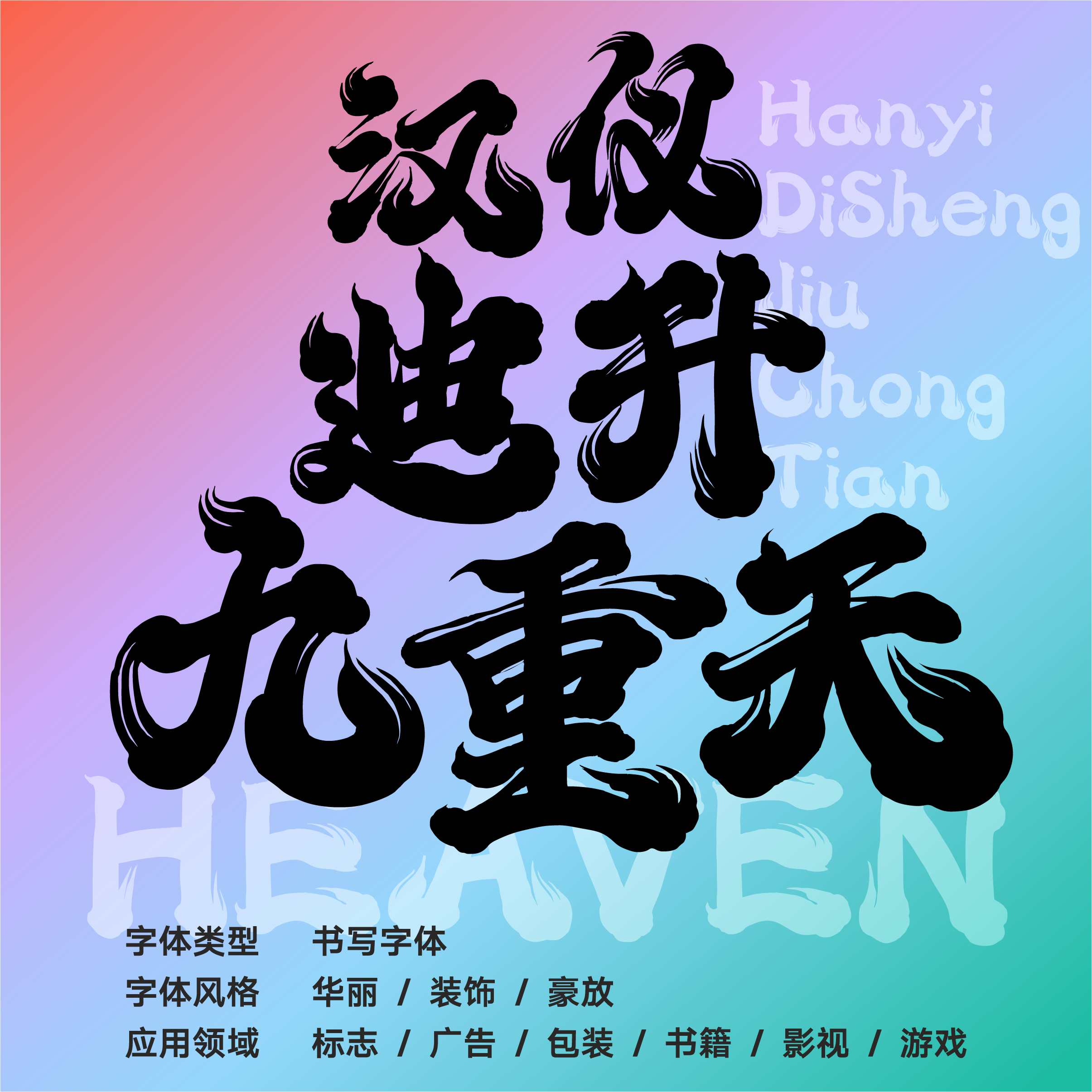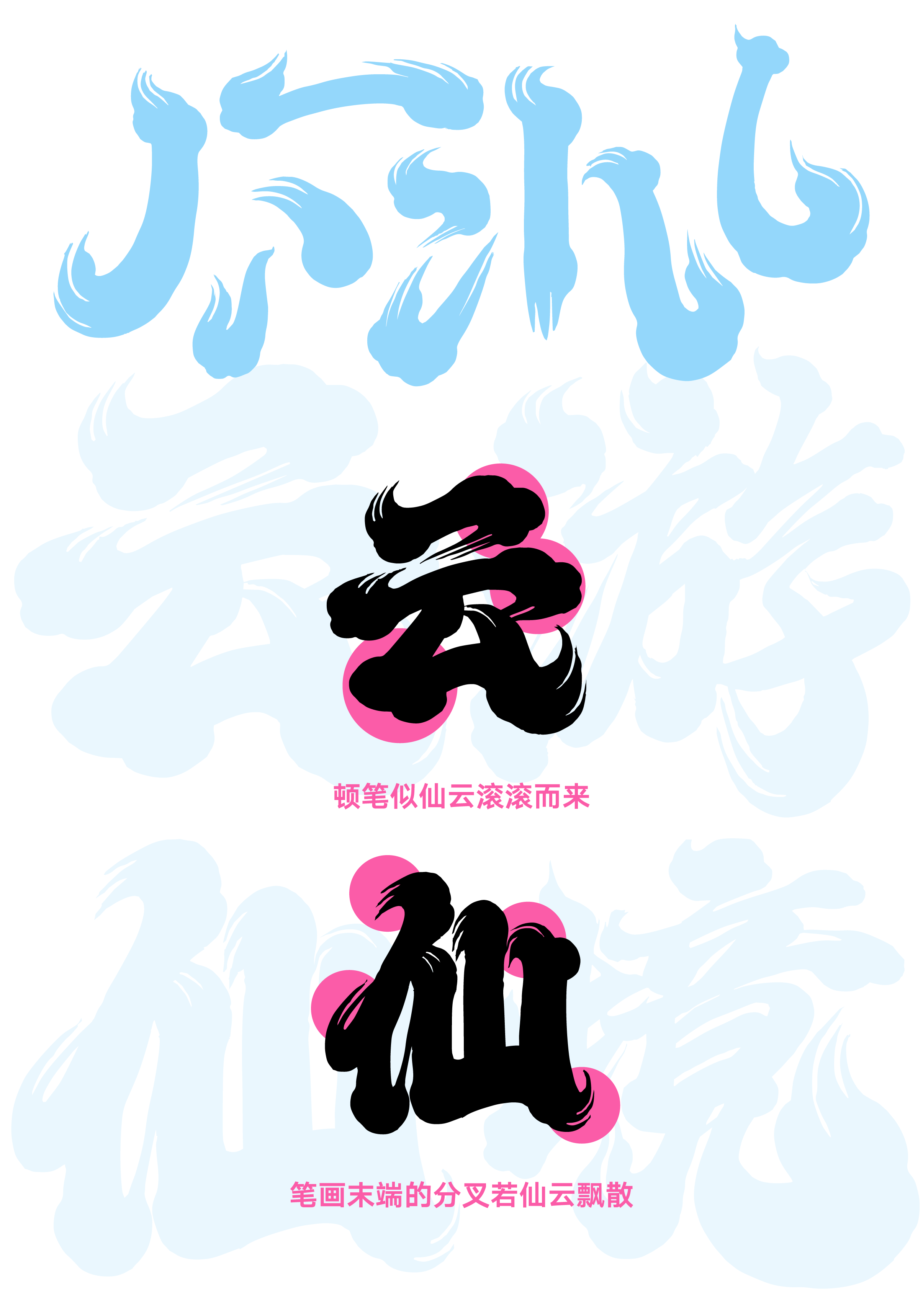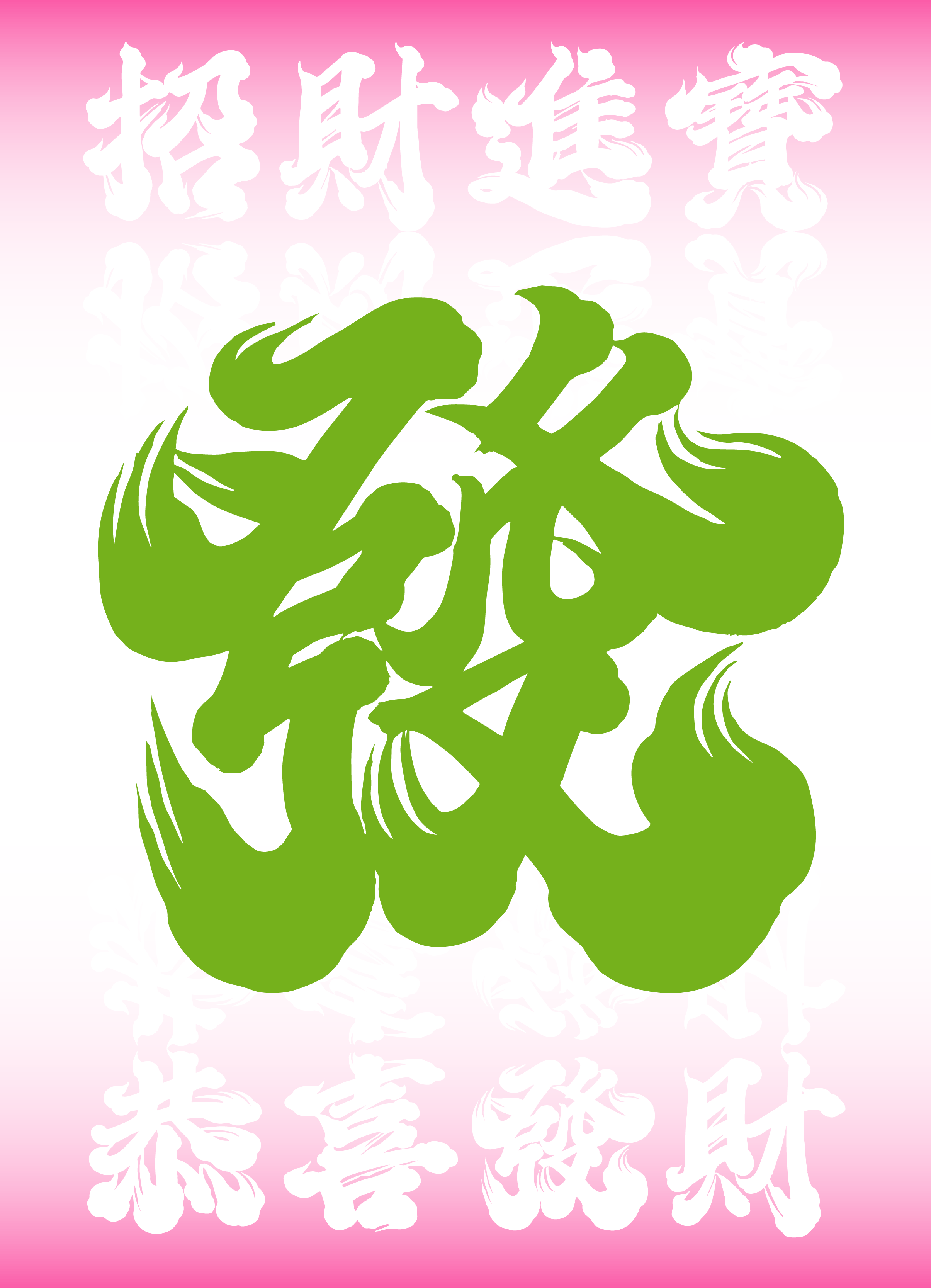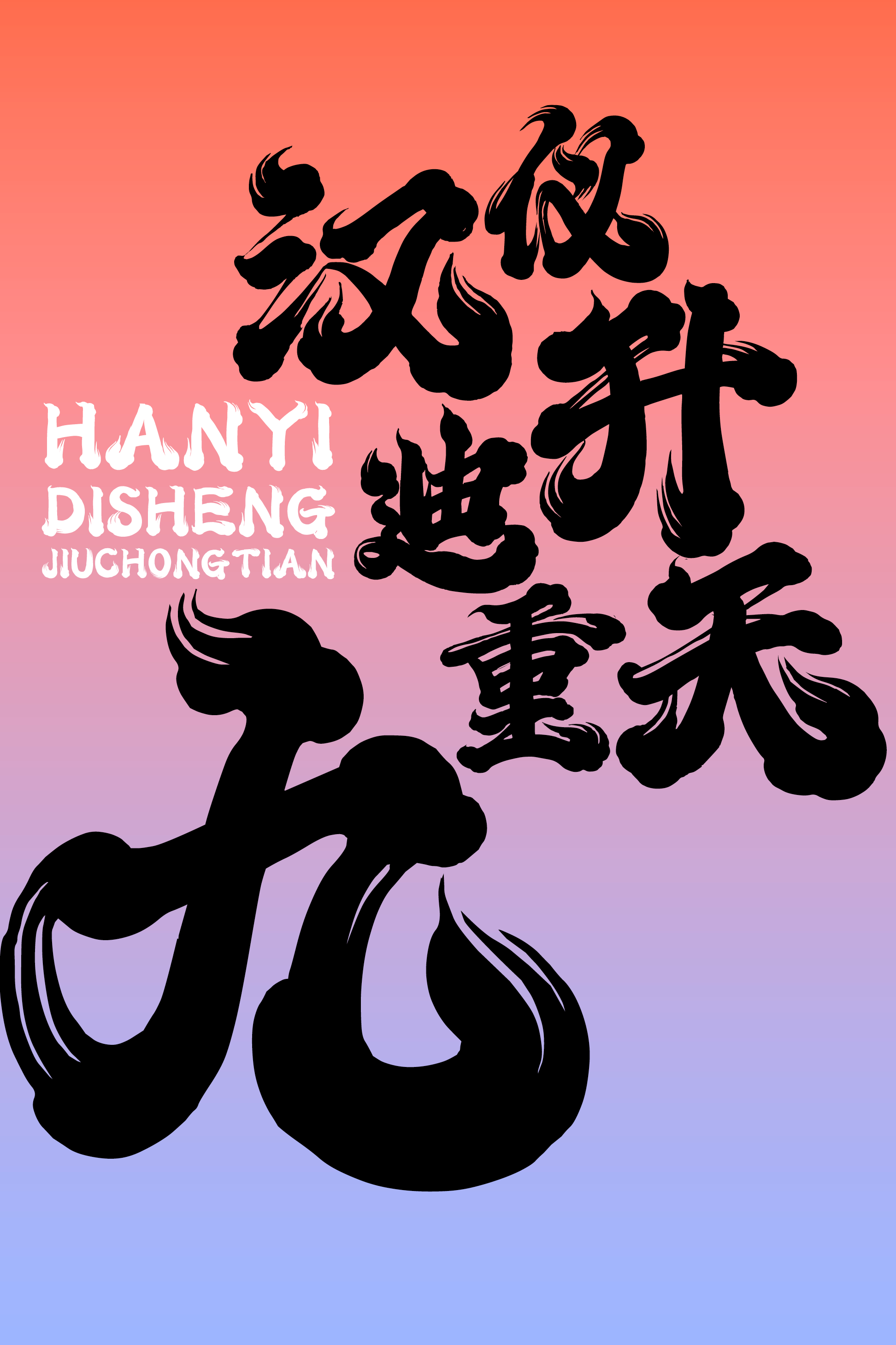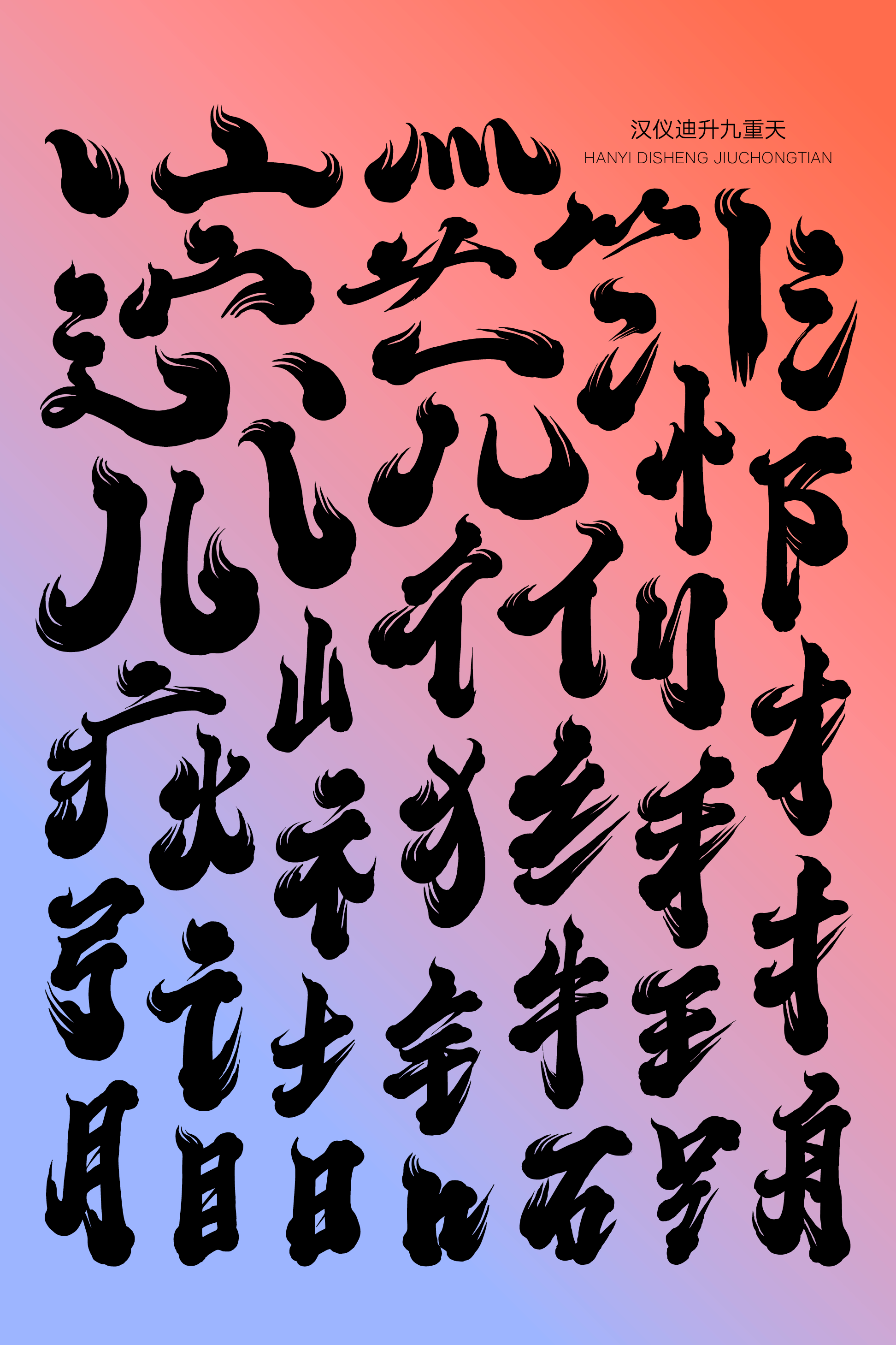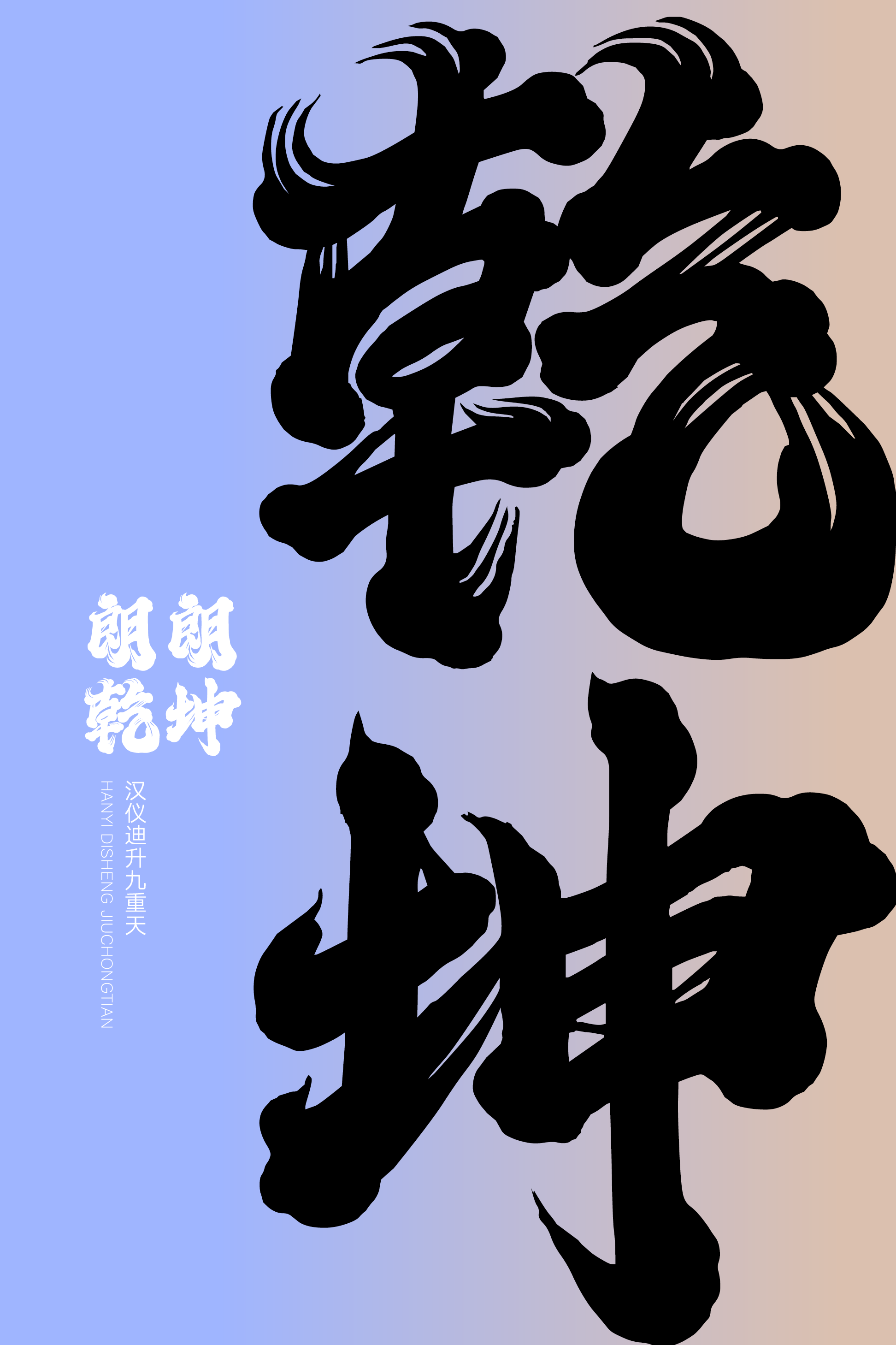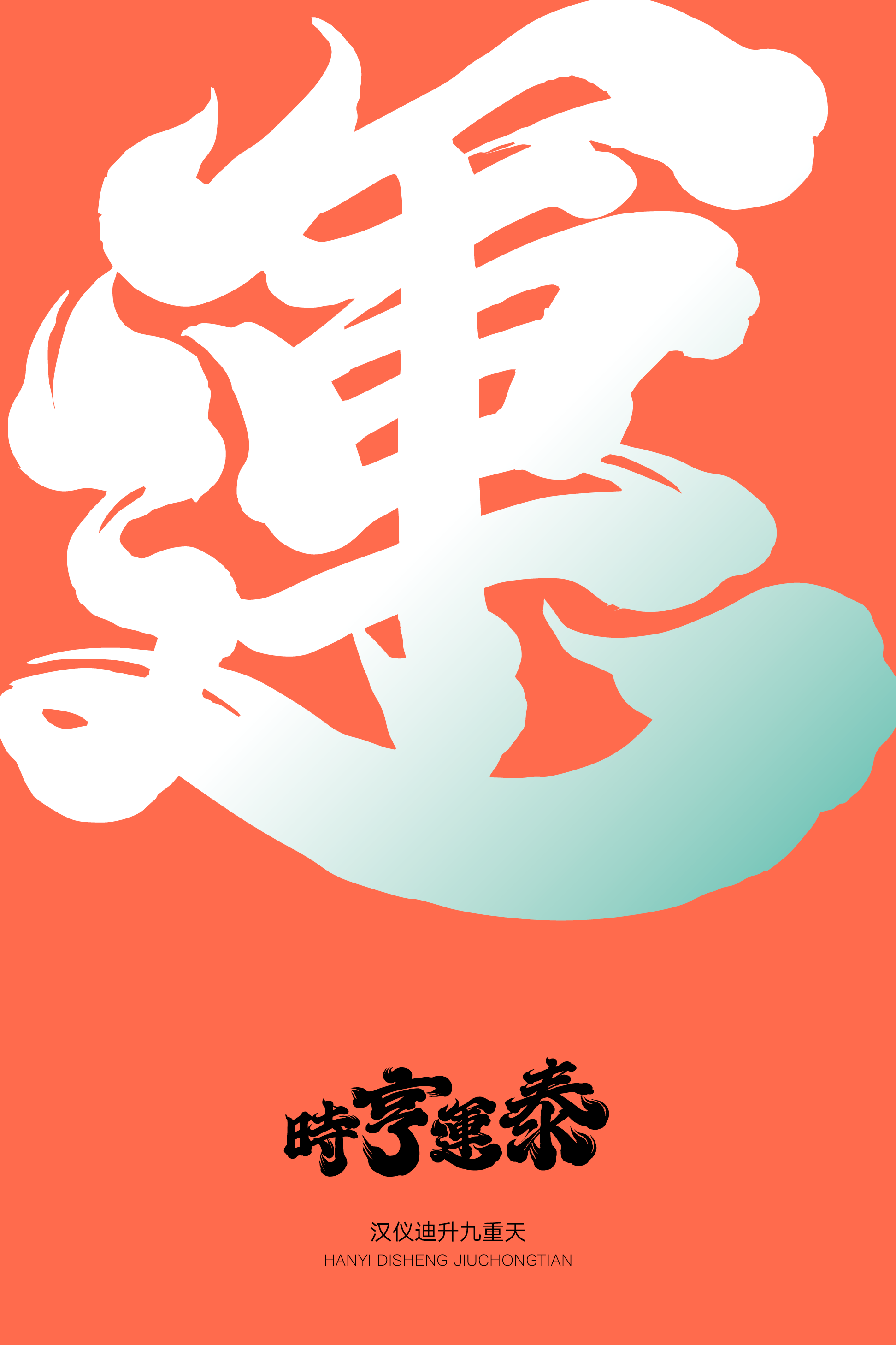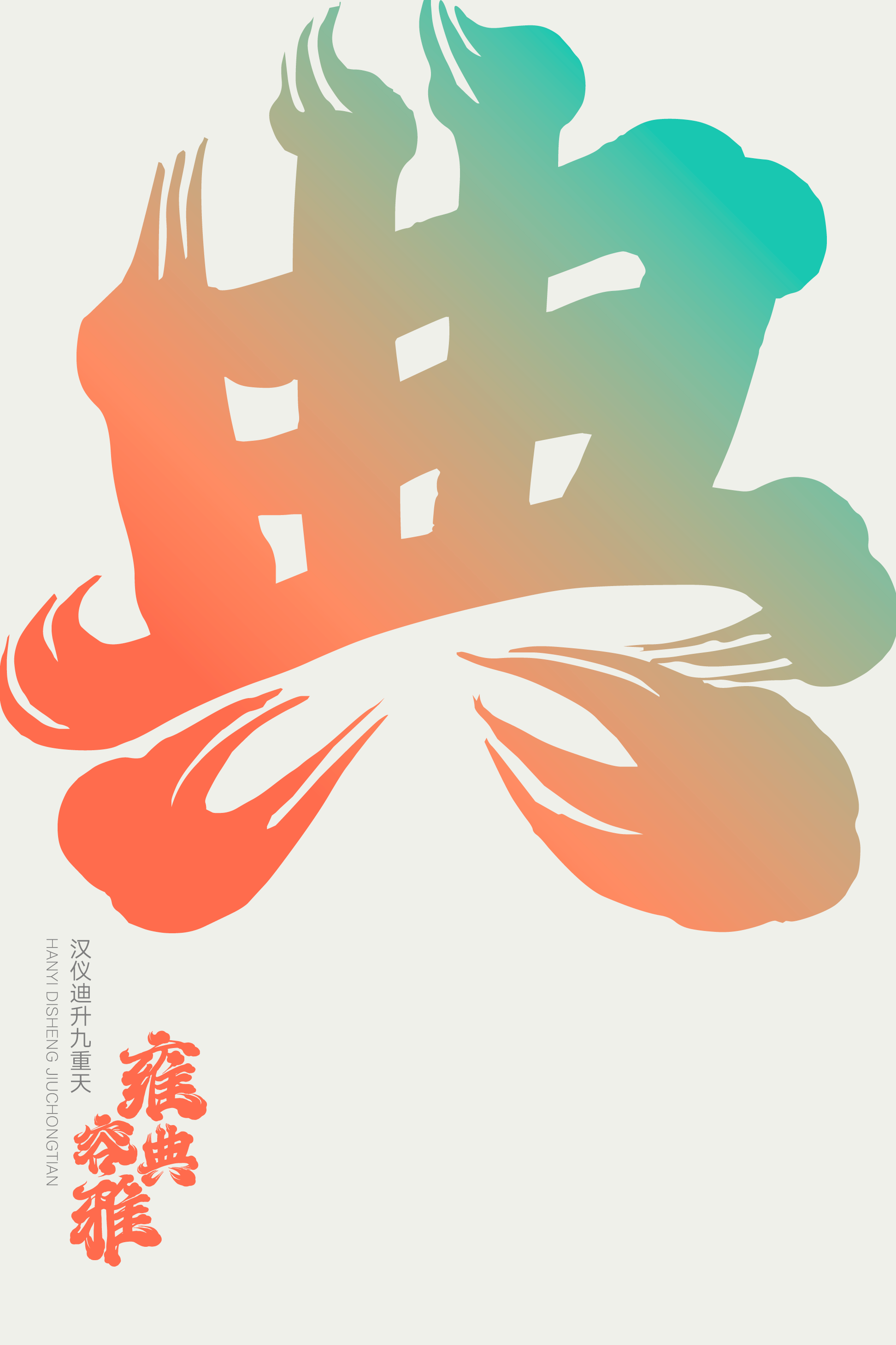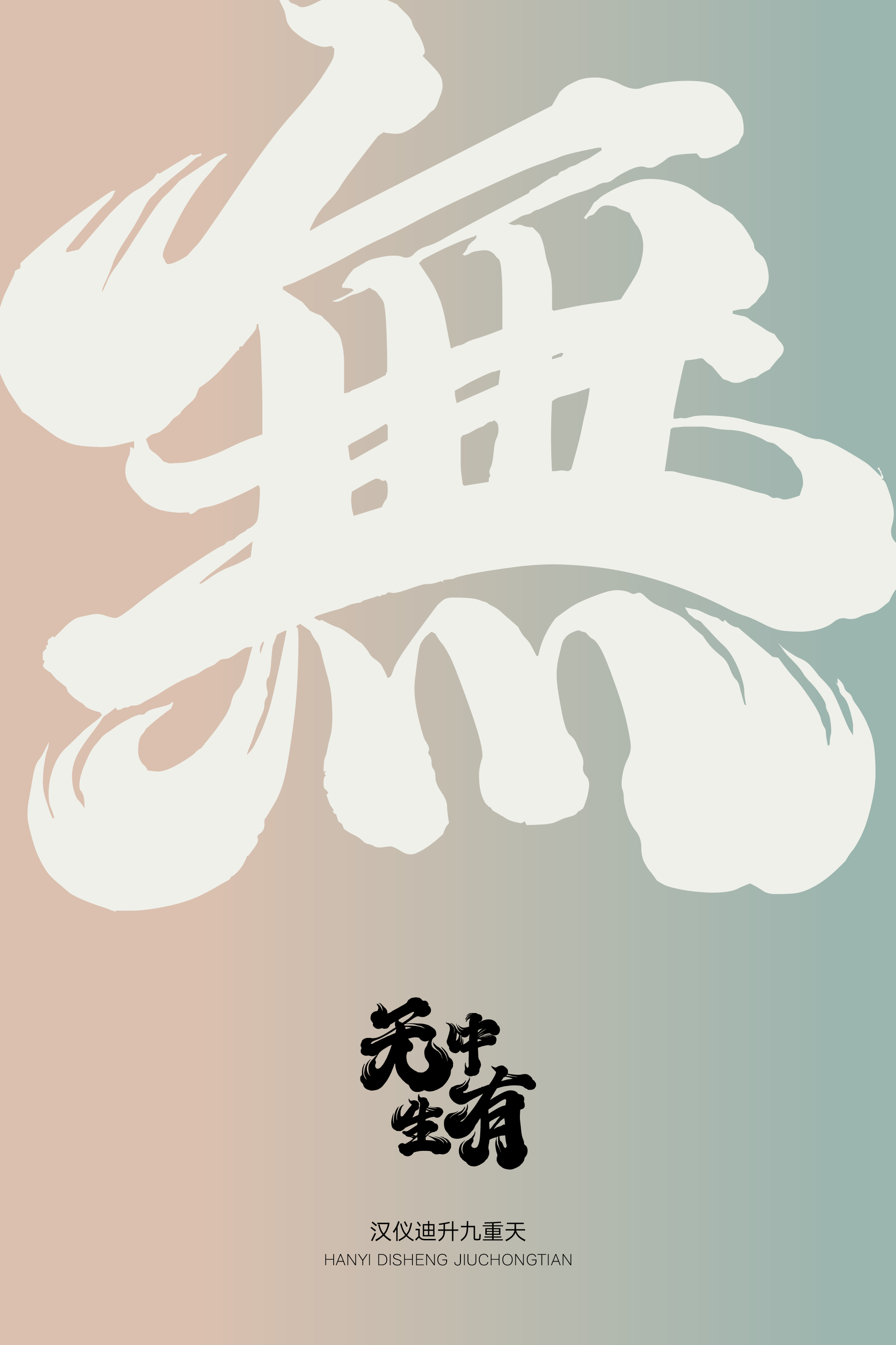
一款自带仙界特效的字体
九重天,传说天有九霄,九有极限之意,指天有多极多重。
汉仪迪升九重天,华美大气,豪放潇洒,气势直冲九霄之上,极尽精致。汉仪字库签约作者迪升创作的这款书写字体华丽而生动,令人仿若置身云间仙境,带来奇幻的视觉体验。这款字体的仙云纹饰颇具传统味道,又显繁华喧腾,与传统节庆的氛围极为相称,适合作为标题或放大单字以更好地展现字体的绘写细节。
华美大气,豪放潇洒。字形顶部微收,底部豪迈外放。
重心提升,中宫紧收,字形向右上方扬起,整体呈仙云翻滚飞升状。
笔画饰以华丽的仙云纹,仙气缭绕,奇幻而神秘。
笔势连贯,一气呵成。保留绘写的痕迹。
汉仪迪升九重天的西文部分以相同的笔法书写,中西文的字形、笔画风格一致,搭配使用自然和谐。
汉仪迪升九重天丰富的绘写细节在大字号环境下展现效果更佳,颇具传统味道的仙云纹饰与传统节庆的氛围极为相称,放大具有美好寓意的单字也可以传达华美之感。